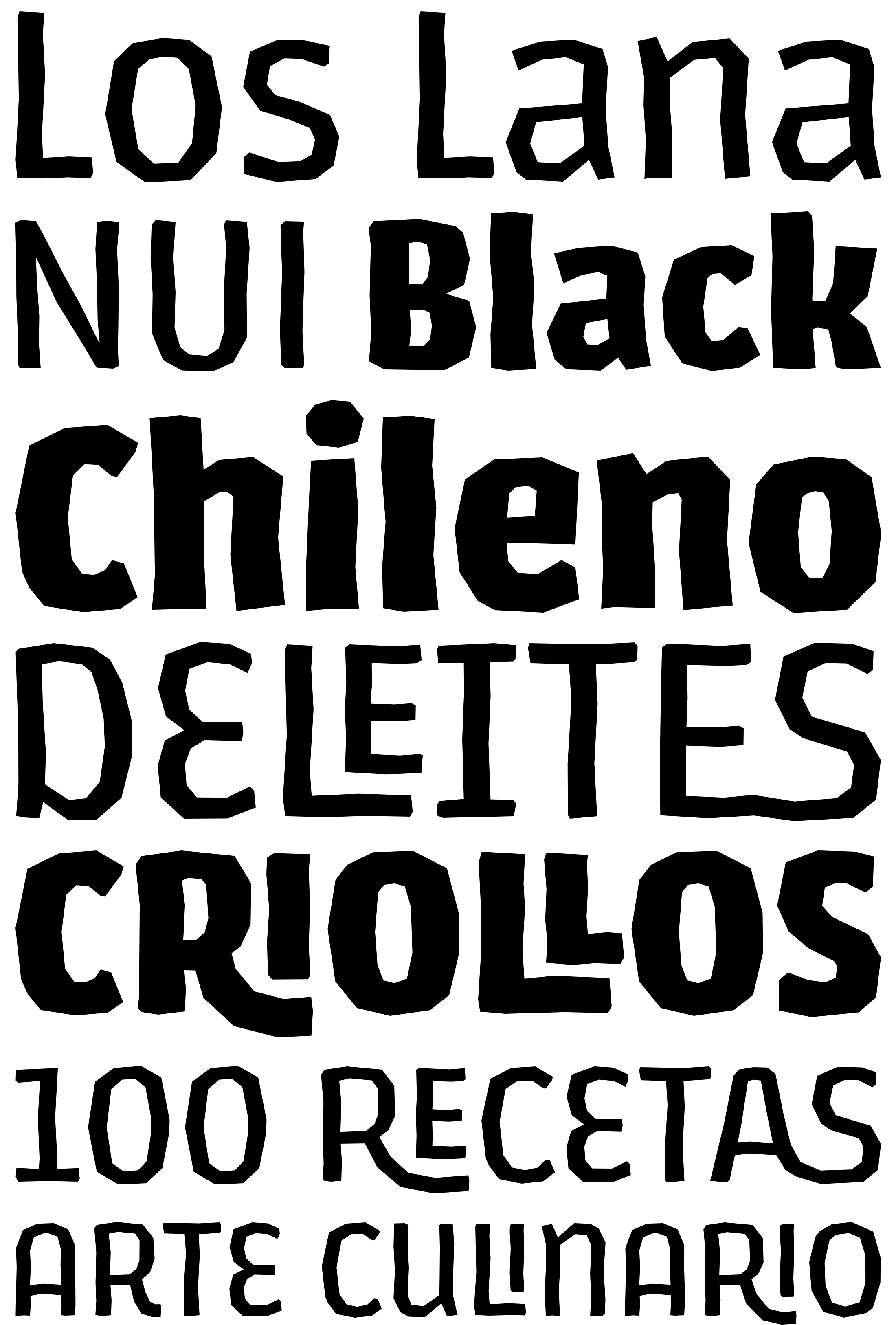
LosLana Niu Pro
| Créditos | Luciano Vergara, Bruno Jara |
| Descripción | Los Lana Niu Pro se basa en Los Lana (2007). Esta nueva versión conserva la estética rústica del tipo de letra original, pero carece de curvas y visualmente parece una fuente irregular. |